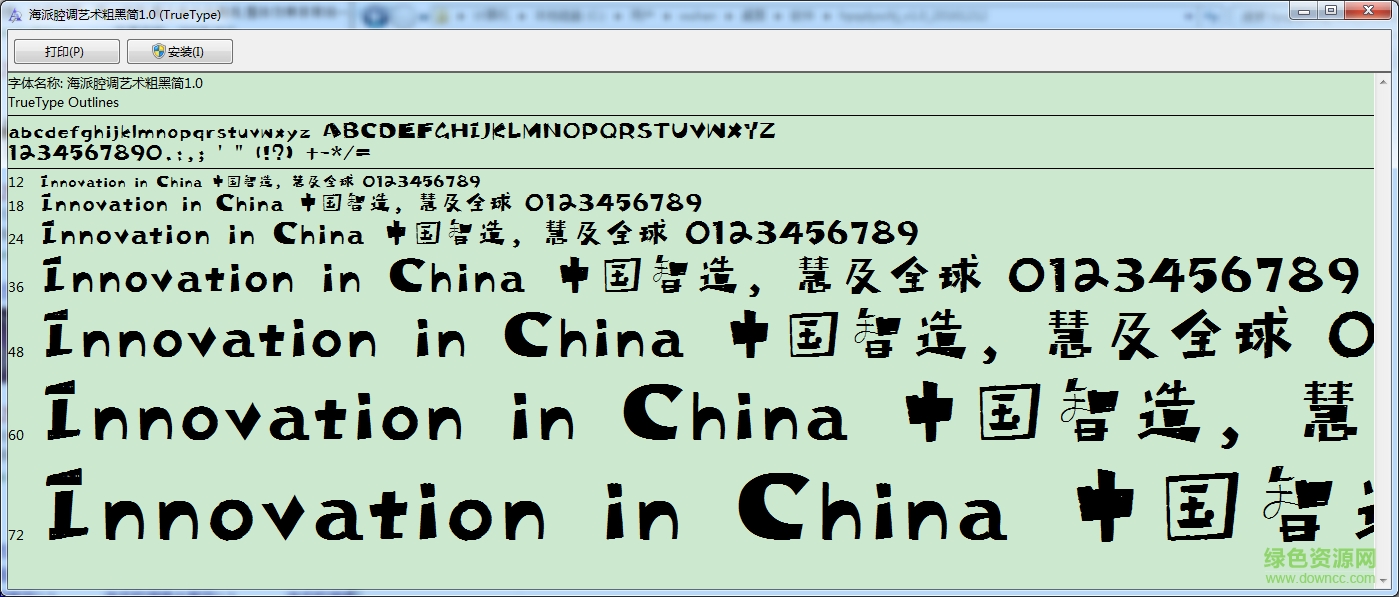
软件介绍 软件标签: shanghaiface字体 海派腔调字体 shanghaiface art boldgb1.0字体又叫海派腔调艺术粗黑,这款字体粗细相间,浓墨重彩,非常有特色,适合用在海报设计或是地方文化宣传手册上,喜欢这款字体的朋友快来下载吧!中文字体的笔形宋体就是以一套宋体的笔形构成,黑体就是以—套黑体的笔形构成,但相对于创意性个体,就可以根据不同创意源点进行变换,通过种种变换手法的处理,往往能带来别具一格的新型字形。shanghaiface字体推荐shanghaiface zen boldgb2.0 授权:免费软件 WinAll, WinXP, Win7大小:2.4M语言:中文shanghaifacezenboldgb2.0字体就是海派腔调禅粗黑简2.0,这款字体特征鲜明,结构设计新颖,非常有范,可用于广告设计或创意设计,有需要者欢迎免费下载!字体设计的技巧【加减法的运用】我们在设计笔画较少的文字下载地址shanghaiface zen extraboldgb2.0字体 授权:免费软件 WinAll, WinXP, Win7大小:5.6M语言:中文shanghaifacezenextraboldgb1.0和2.0两款字体是绿色资源网为大家搜集的海派腔调禅大黑简合集下载包,结构紧凑,疏密设计精巧,粗细对比强烈,非常有韵味,欢迎下载!海派腔调禅大黑简特点字体粗细度采用了粗的Bold的下载地址字体安装方法方法一:控制面板/字体/文件/安装新字体;方法二:直接将字体复制到C:\WINDOWS\Fonts。方法三:针对win7系统,用户只需选中字体右键安装即可。 软件截图 上一张下一张(1 / 1) 安装详细截图 其他版本下载 标题 大小 更新日期 下载 下载地址 电脑版 shanghaiface art boldgb1.0 点击报错 软件无法下载或下载后无法使用,请点击报错,谢谢! 关闭报错反馈 请描述您所遇到的错误,我们将尽快予以修正,谢谢! *必填项,请输入内容 本类最新 dreamweaver字体库 首尔南山体字体 v1.06 官方版 潮字社风云简ttf 潮字社凌渡鲲鹏简体字体 潮字社曾玉波手书简字体 微博慧心字体 相关文章 用CMailServer打造邮件服务器 用好SATAII硬盘,使用技巧详解 GHOSTXP光盘刻录图文教程 (傻瓜式多图) Ghost的使用:记住口诀,就这么的简单 GHOST误操作导致分区丢失的恢复教程 使用Windows 7备份Ghost注意事项 用户评论 热门评论 最新评论 发表评论 查看所有评论(0) 昵称: 请不要评论无意义或脏话,我们所有评论会有人工审核. 字数: 0/500 (您的评论需要经过审核才能显示)